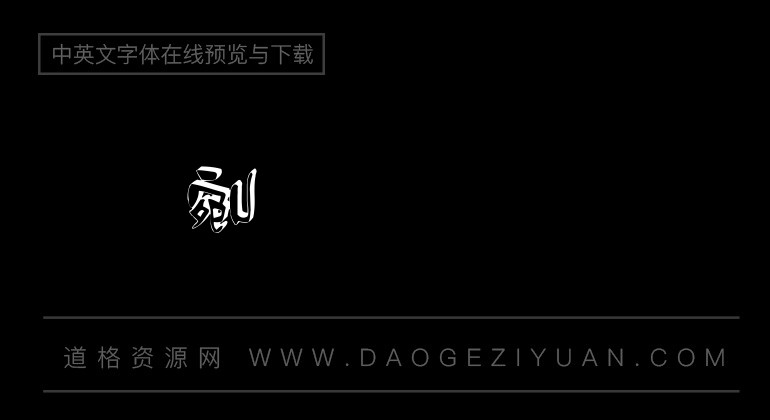
金梅浪漫白立体
? 金梅浪漫白立体字体是一款由金梅字体设计团队开发的立体字体,主要以梅花为原型,结合传统的立体字体设计,使字体具有浪漫、温馨的气息。字体笔画粗细适中,结构精细,可以更好地表达文字的意义,适用于各种排版,且占用空间较小,是网页设计师的首选字体。
金梅浪漫白立体是一款非常不错的手写艺术字体,具有很好的视觉感,适合于文化类的宣传设计、商业类品牌的广告和产品包装设计以及个性化文字排版等较多场景。